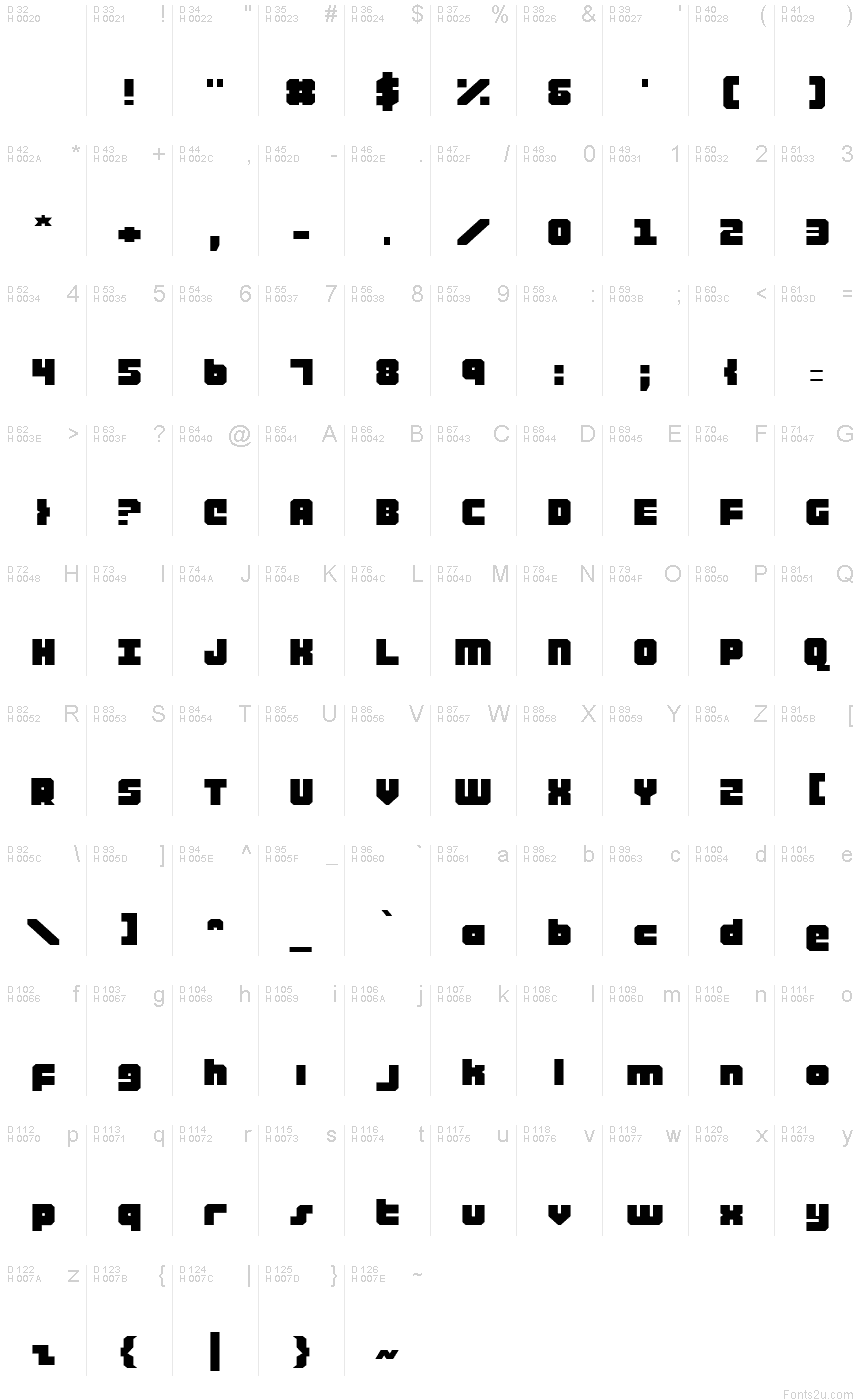
Alpha Taurus Expanded od Iconian Fonts to darmowy font typu techno display o surowej, arkadowej stylistyce. Litery zbudowane są z masywnych, wielokątnych bloków o ściętych rogach i kwadratowych wycięciach, co nadaje całości twardy, robotyczny rytm, przypominający bardziej logotypy starych gier i panele sterowania sci-fi niż neutralne kroje wystawowe.
Świetnie sprawdzi się na plakatach, w tytułach gier, grafikach esportowych, okładkach albumów czy w ostrym brandingu, gdzie krótkie słowa wymagają tego syntetycznego wyglądu „stemplowanego maszynowo”. Jako darmowy font, doskonale nadaje się również do plansz tytułowych i krótkich nagłówków, ponieważ powtarzalne nacięcia i pudełkowate otwory sprawiają, że nawet proste wyrazy zyskują zakodowany, futurystyczny charakter.